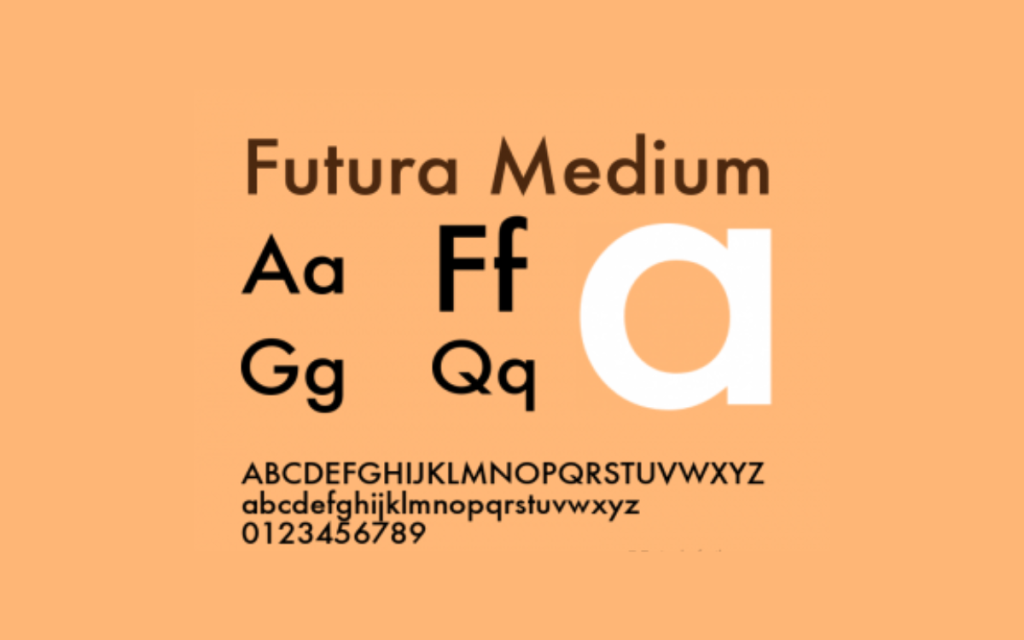
Font Futura Medium
Tác giả: Paul Renner
Ngày phát hành: 1927
Bộ Font: Font Futura
Phân loại: Cổ điển
Độ dày: Medium
Font Futura Medium là một font chữ thuộc bộ font chữ không chân, nổi bật với thiết kế gọn gàng và hiện đại. Được tạo ra bởi Paul Renner vào năm 1927, Font Futura Medium mang đến sự cân đối hoàn hảo giữa tính hình học và tính thẩm mỹ, tạo nên cảm giác chuyên nghiệp và đáng tin cậy cho các dự án thiết kế. Nhờ vào sự dễ đọc và đường nét tinh tế, font chữ này thường được sử dụng rộng rãi trong các lĩnh vực như thiết kế đồ họa, quảng cáo, và thương hiệu, mang lại hiệu quả cao trong việc truyền tải thông điệp một cách mạnh mẽ và rõ ràng.